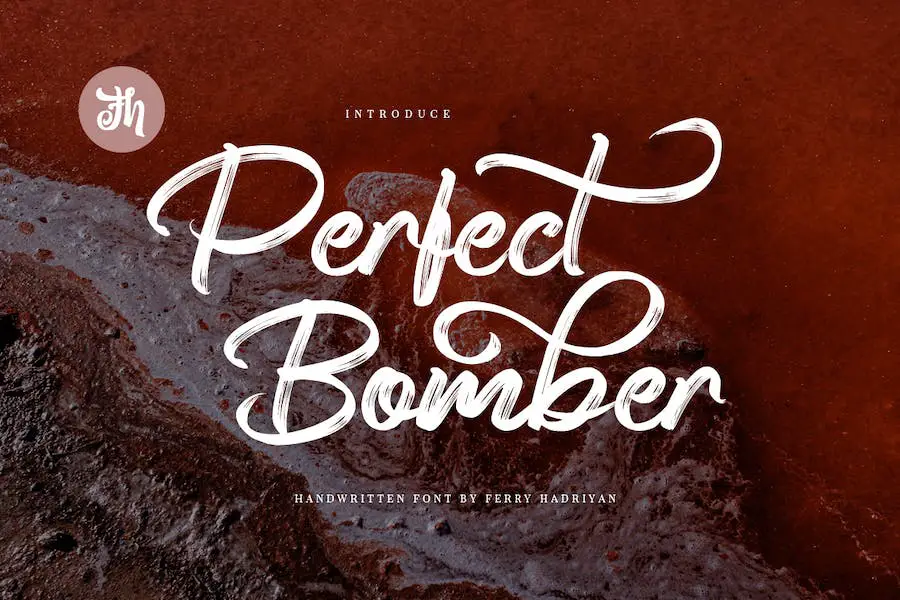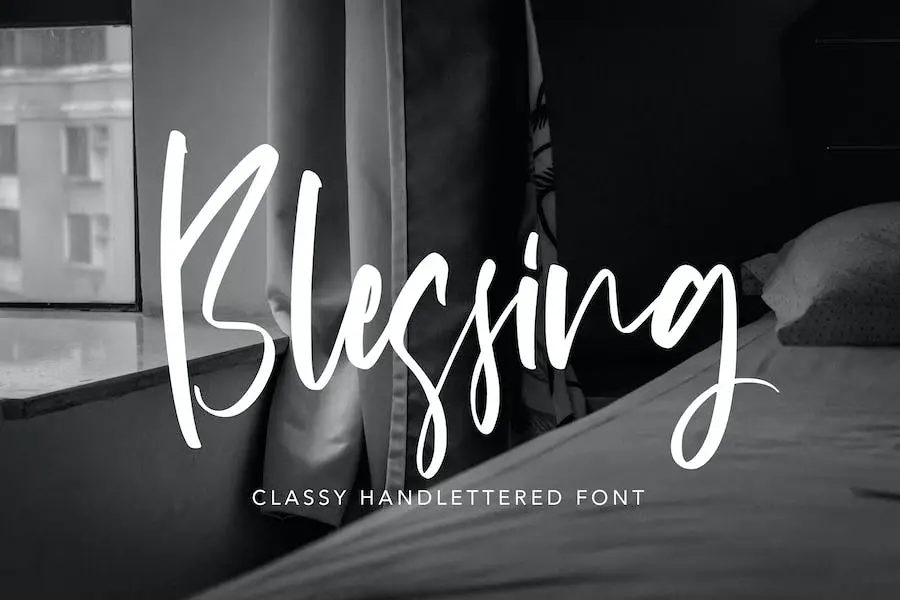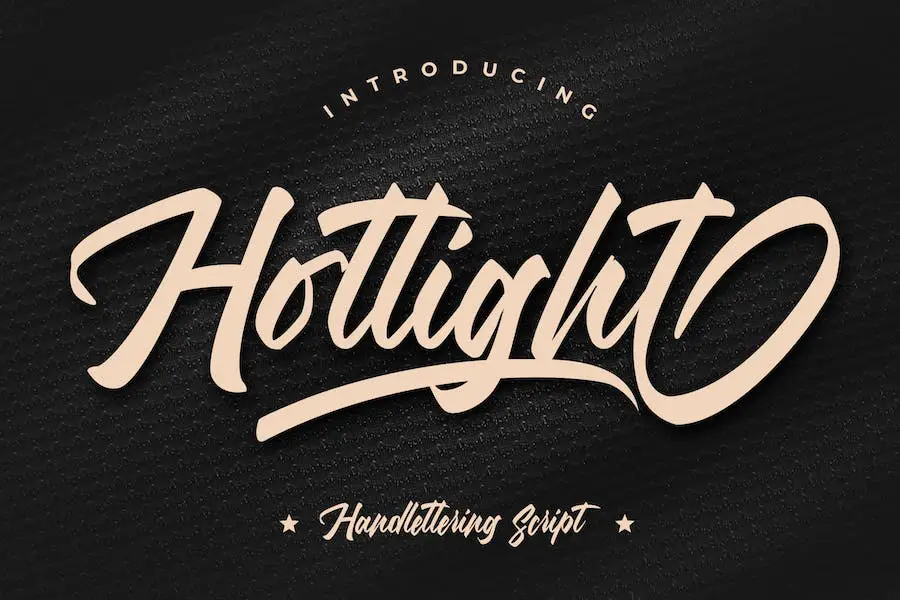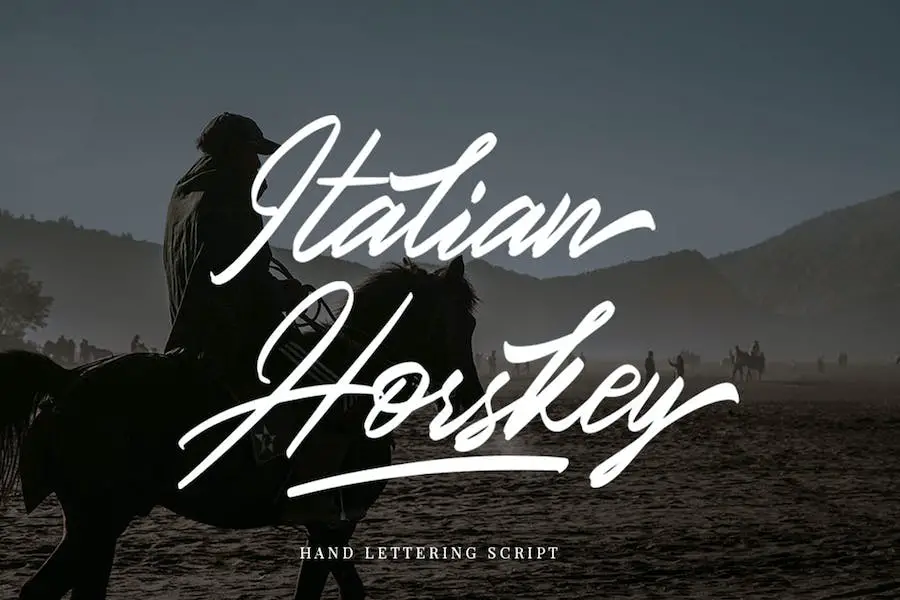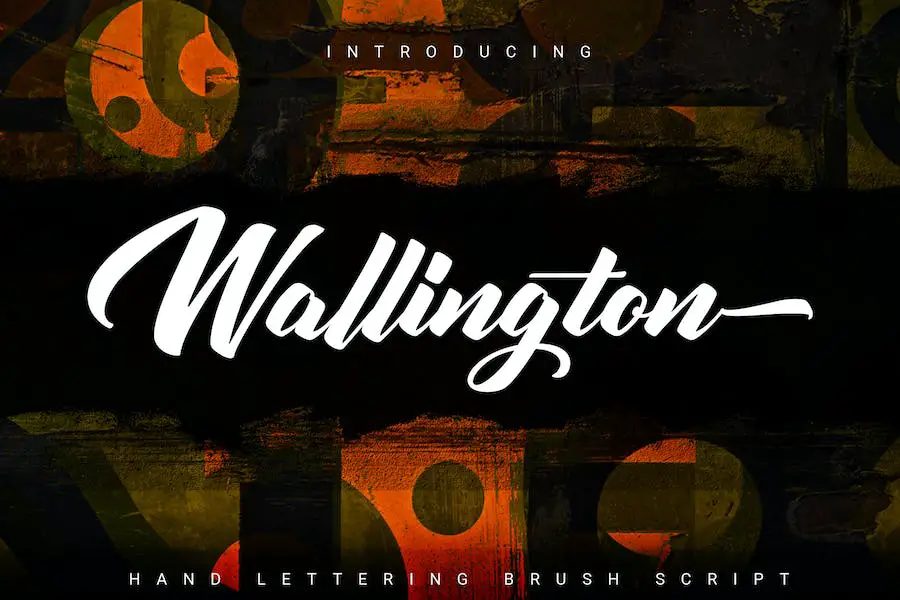
37 melhores fontes para letras manuais 2023 (gratuitas e premium)
Publicados: 2023-10-02Você é um designer gráfico que busca aprimorar o design de seus projetos? Você está procurando as melhores fontes de letras manuais para adicionar um toque de elegância e criatividade ao seu trabalho? Não procure mais!
Nesta postagem do blog, selecionamos uma lista das 37 melhores fontes de letras manuais para o ano de 2023, incluindo opções gratuitas e premium.
Esteja você trabalhando em um logotipo, design de site ou qualquer outro projeto gráfico, essas fontes certamente elevarão seus designs ao próximo nível.
Neste artigo, não apenas apresentaremos uma ampla variedade de fontes de letras manuais, mas também forneceremos algumas estatísticas e fatos valiosos sobre cada fonte.
Entendemos que, como designer gráfico, você deseja tomar decisões informadas quando se trata de escolher a fonte certa para o seu projeto. É por isso que fizemos a pesquisa para você, para que você possa economizar tempo e se concentrar no que faz de melhor: projetar.
Sem mais delongas, vamos mergulhar no maravilhoso mundo das fontes de letras manuais! Nas seções a seguir, mostraremos cada fonte individualmente, destacando seus recursos exclusivos, conjuntos de caracteres e dicas de uso.
Quer você seja um designer experiente ou esteja apenas começando, este artigo servirá como um guia completo para ajudá-lo a encontrar a fonte de letras manuscritas perfeita para seu próximo projeto. Então, vamos começar e descobrir a fonte que levará seus designs a novos patamares!
As melhores fontes premium para letras manuais
Quer adicionar um pouco de talento e personalidade aos seus projetos de design? Não procure mais, nossa seleção escolhida a dedo das melhores fontes premium de letras manuais.
Essas fontes certamente elevarão seus designs e impressionarão seus clientes. Então, por que esperar? Mergulhe em nossa coleção selecionada e descubra a fonte perfeita para seu próximo projeto.
Santoy
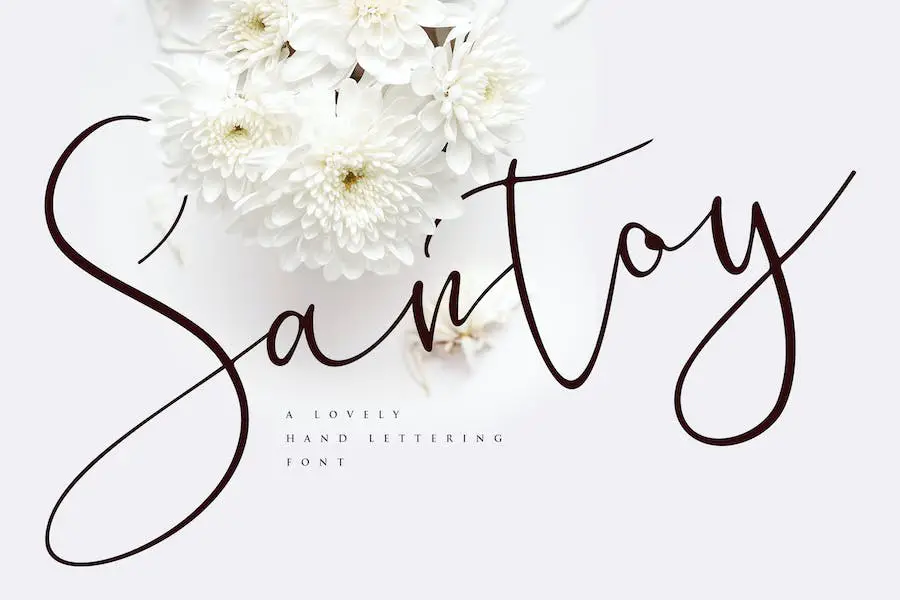
Santoy é uma fonte impressionante para letras manuais que adiciona um toque de elegância e criatividade aos seus projetos de design. Com seu estilo de caligrafia, é perfeito para uso em convites, cartões comemorativos, materiais de branding, cartões de visita, citações, pôsteres e muito mais!
A versatilidade do Santoy o torna adequado para uma ampla gama de finalidades de design. Esteja você trabalhando em um convite de casamento, um cartão de Natal ou um pôster promocional, essa fonte elevará seu design e o destacará.
Com sua estética desenhada à mão, Santoy acrescenta um toque pessoal e artístico às suas criações. Os traços fluidos e os detalhes intrincados das letras dão ao seu texto uma sensação de habilidade e exclusividade.
Letras de cerefólio
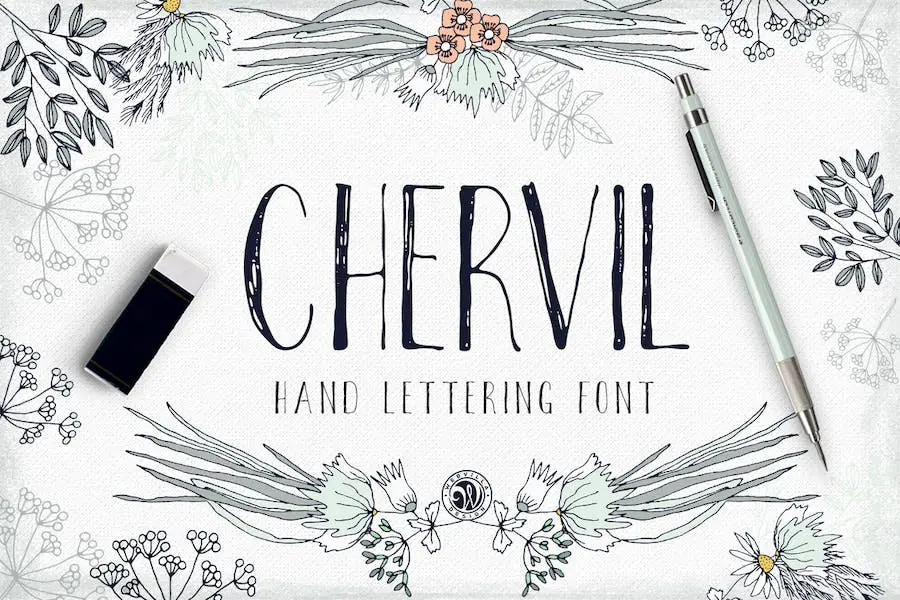
A fonte Chervil hand lettering é uma ferramenta versátil que elevará seus projetos de design gráfico para o próximo nível.
Com seus traços elegantes e artísticos, é perfeito para adicionar um toque de sofisticação a convites, logotipos, materiais de branding, blogs, artesanatos, scrapbooking e itens de papel impresso.
Esta fonte oferece infinitas possibilidades de expressão criativa e certamente fará com que seus designs se destaquem da multidão.
Férias
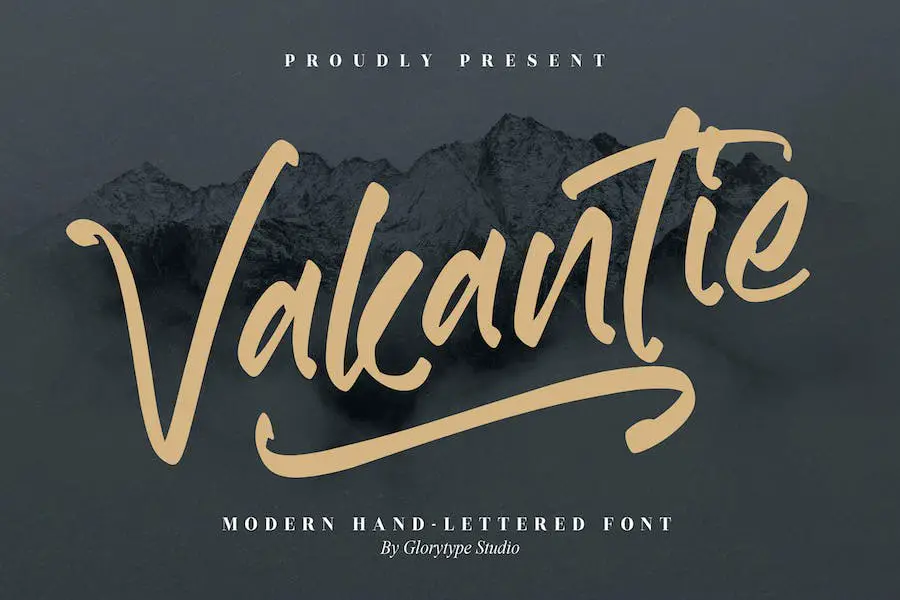
Vakantie é uma fonte projetada para aprimorar a aparência de seus produtos criativos digitais e impressos. É uma escolha versátil que funciona bem para uma variedade de projetos, como pôsteres, postagens em mídias sociais, branding e empreendimentos pessoais.
Com seu estilo único e atenção aos detalhes, Vakantie certamente elevará seus designs ao próximo nível. Seja você um designer gráfico profissional ou alguém que deseja adicionar um toque de criatividade aos seus projetos, esta fonte é obrigatória em seu kit de ferramentas.
Abandono
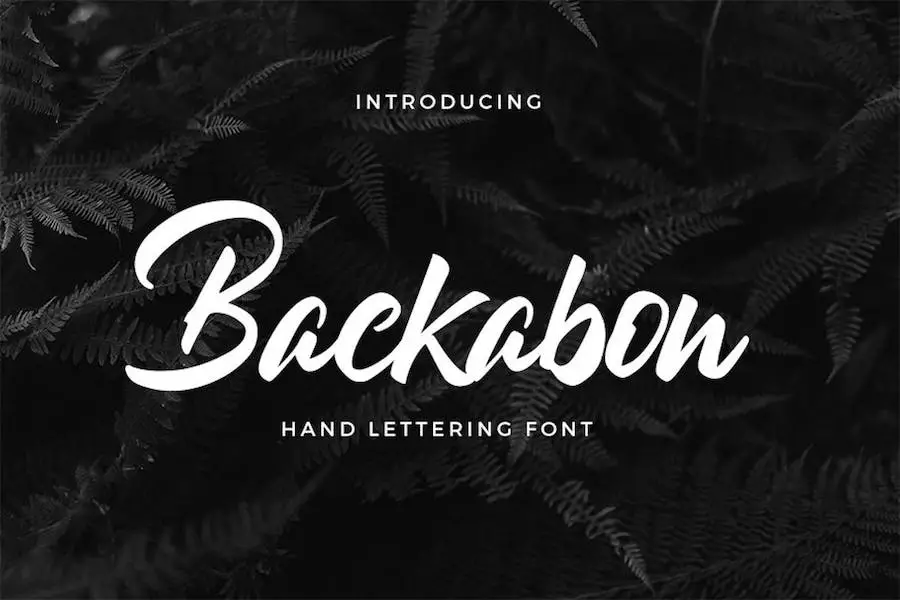
Backabon é uma fonte de script conectada em negrito, perfeita para adicionar um toque de criatividade aos seus projetos de design. Esteja você trabalhando em um logotipo, citações impressas, convites, cartões ou embalagens de produtos, esta fonte fará com que seus designs se destaquem.
Com seu design exclusivo e elegante, Backabon também é ótimo para cabeçalhos, logotipos, papéis timbrados, pôsteres, designs de vestuário, etiquetas e muito mais. Sua versatilidade o torna indispensável para qualquer designer gráfico que busca aprimorar seus projetos.
Regule um Natural
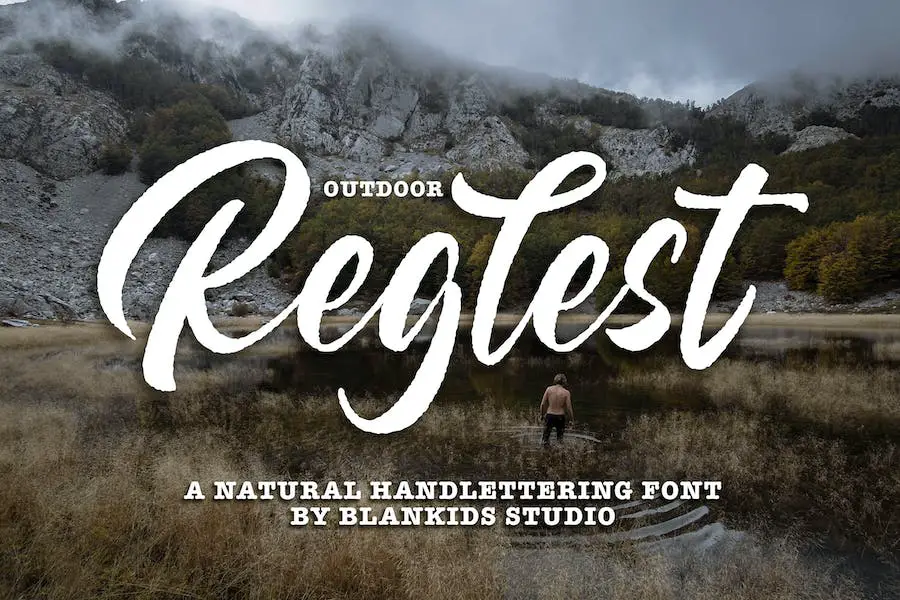
Reglest a Natural é uma fonte moderna de script com letras naturais que o ajudará a criar algo que se destaque e inspire criatividade, imaginação e diversão sem fim.
Esta fonte é inspirada na tipografia do estilo pincel, tornando-a perfeita para designs atraentes e divertidos. Possui alto nível de estética, o que o torna adequado para diversos fins, como capas de livros, pôsteres, embalagens, mercadorias e logotipos.
Com Reglest a Natural, você pode adicionar um toque único aos seus projetos e torná-los visualmente atraentes. Então, se você é um designer gráfico em busca de uma fonte para aprimorar o design do seu projeto, esta é a fonte para você.